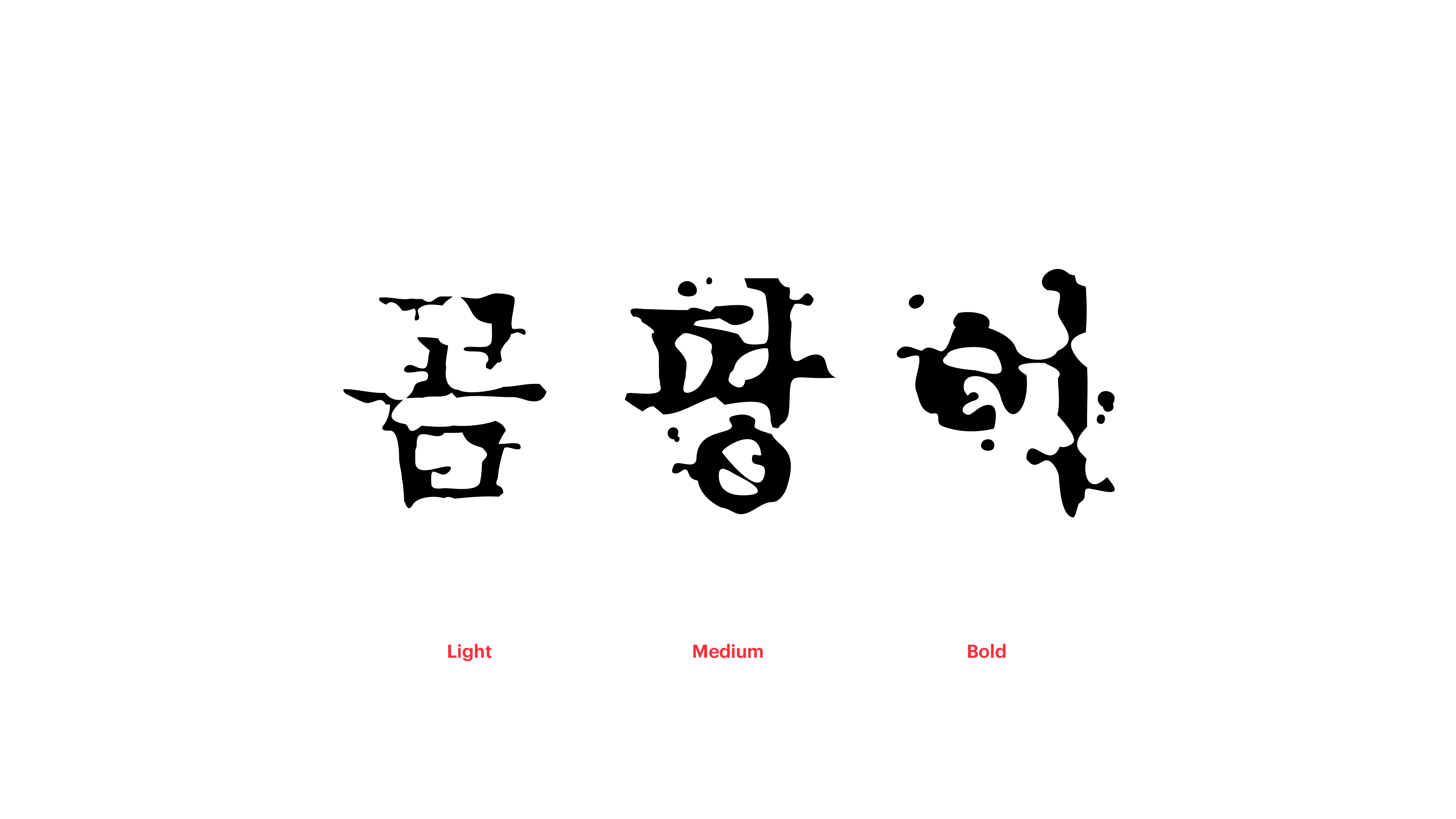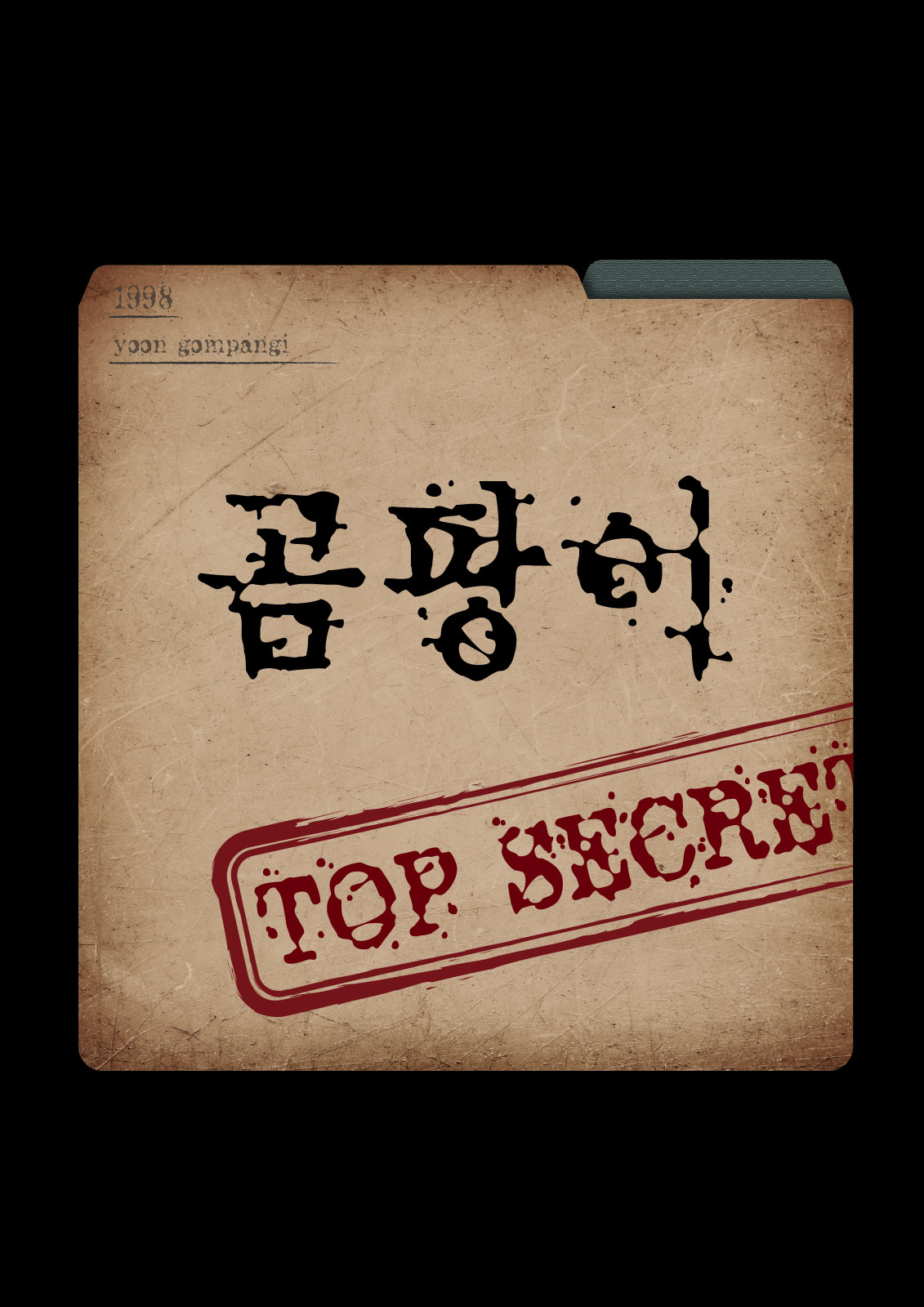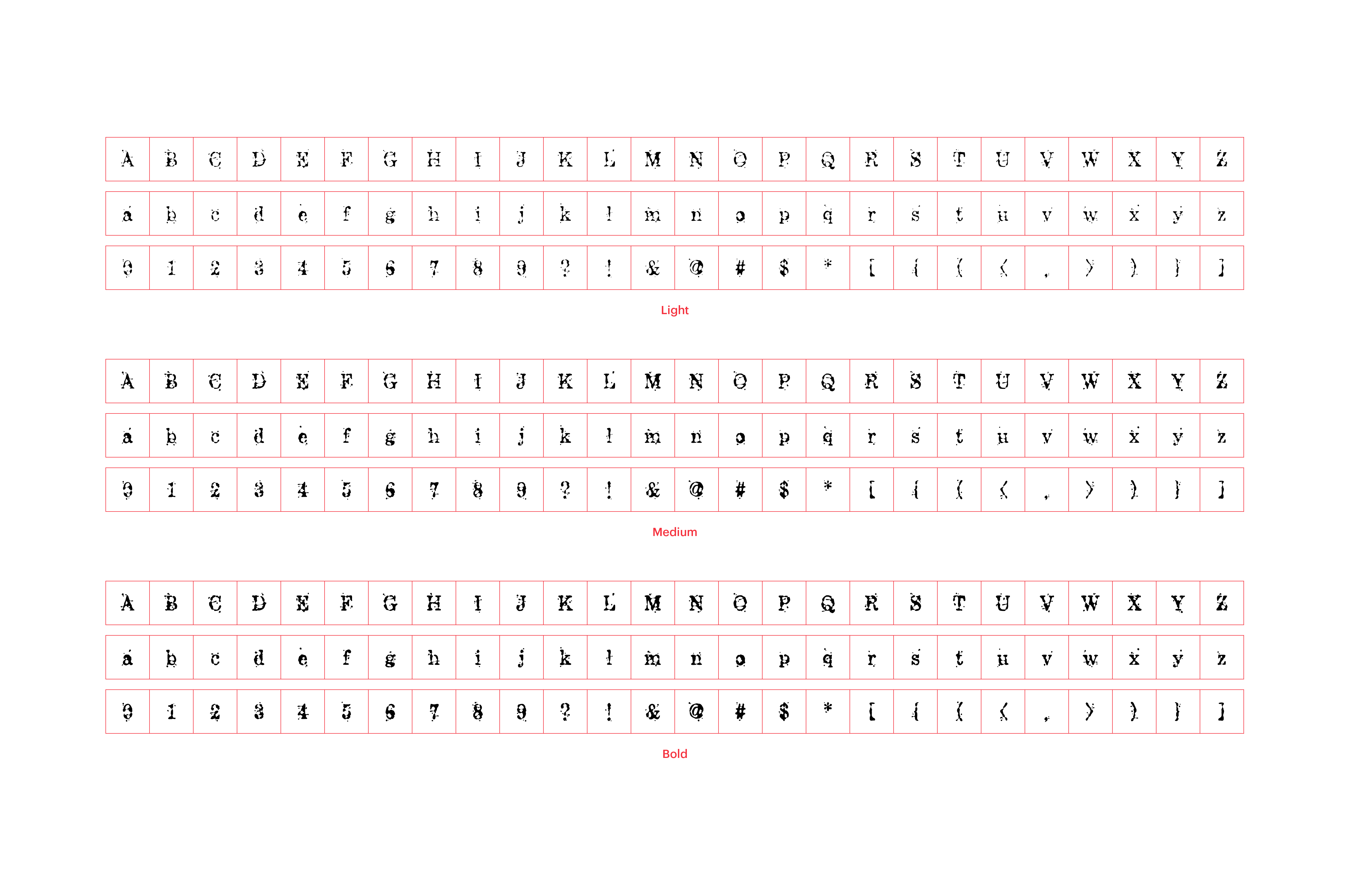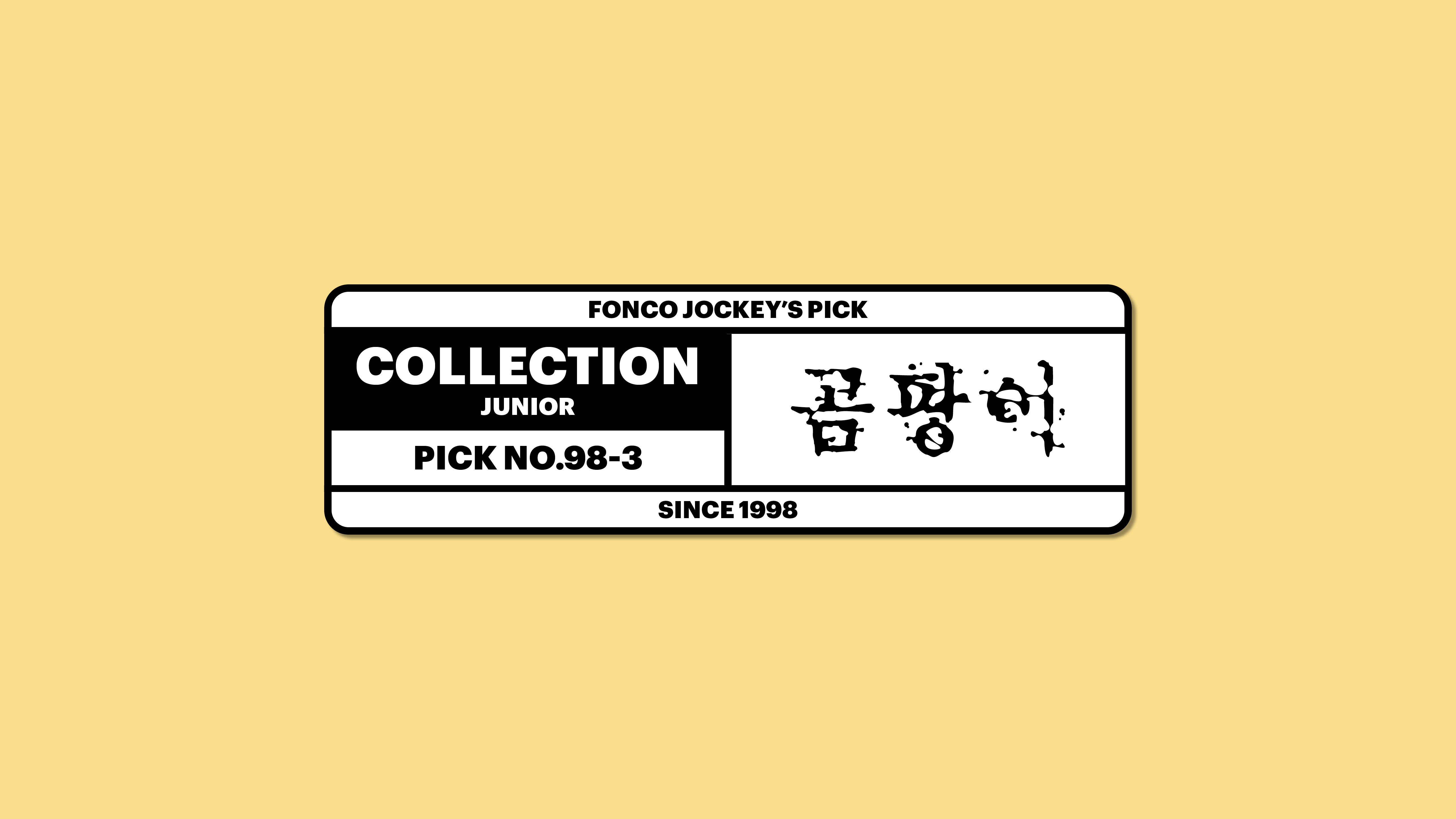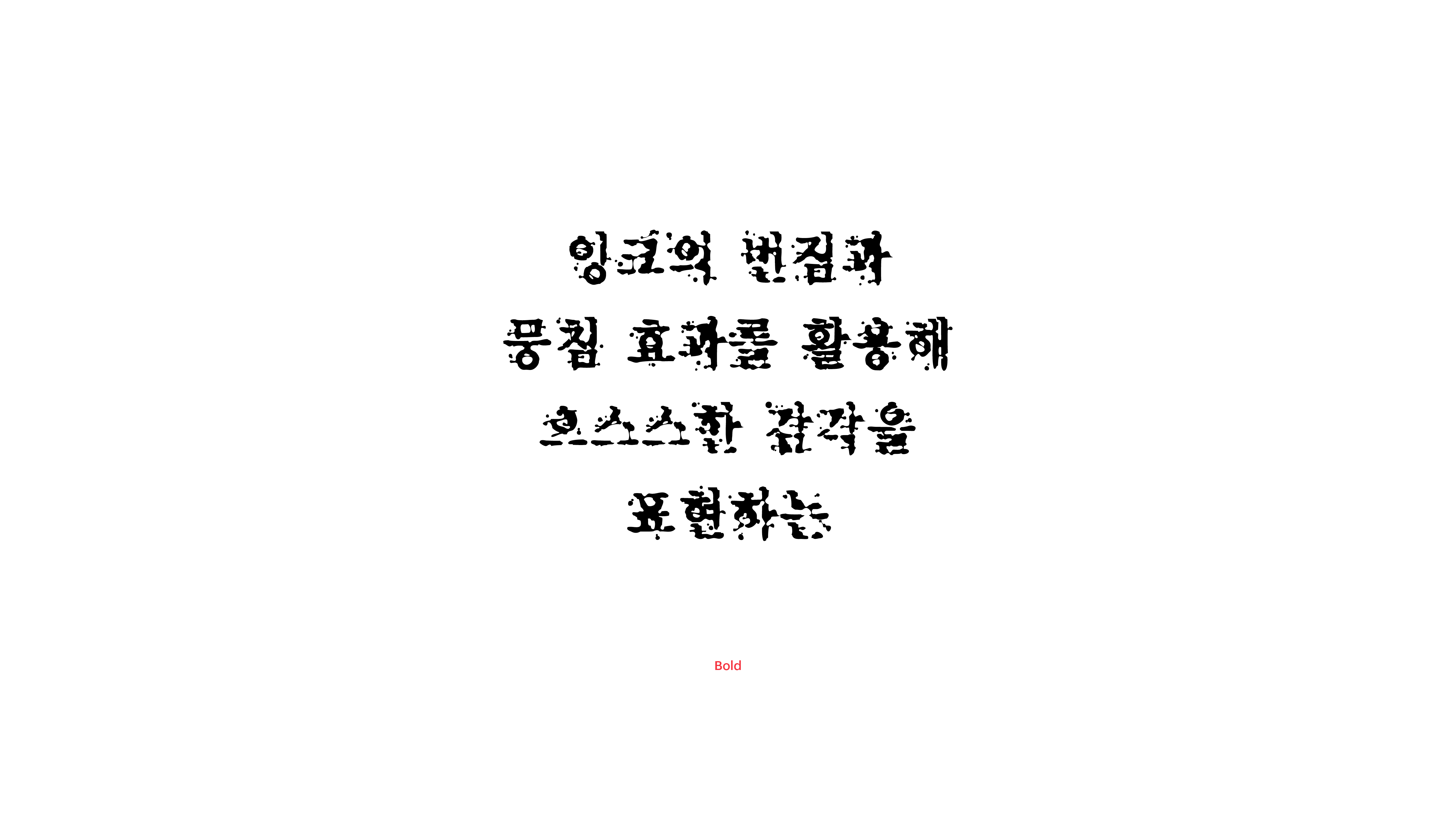
곰팡이
Yoon 곰팡이
한여름 쥐도 새도 모르게 피어나는 곰팡이는 공포의 대상입니다. 무서운 것은 피하는 게 상책이라지만, 피할 수 없을 땐 곰팡이체를 꺼내 제대로 기록해보는 거 어떨까요? 잉크의 번짐과 뭉침 효과를 활용해 으스스한 감각을 환기하는 이 폰트, 진짜 곰팡이도 울고 갈 만큼 꽤 무섭다니까요?